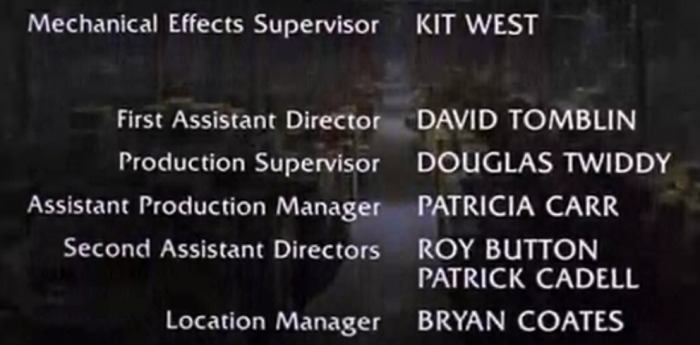
Nachspann aus "Jäger des verlorenen Schatzes"
weiß jemand ganz spontan welche Schrift das hier ist? Ich habe leider nur diesen Screenshot von YouTube, aber ich meine irgendwie, die Schrift zu kennen. Das "a" und das "d" sind durch ihren vom Stamm gelösten Bauch recht auffällig, oder? Ich bin sicher, das weiß jemand wie aus der Pistole geschossen (aus der Hüfte, natürlich).
Auch wenn ich's erwartet hatte, ich bin beeindruckt. Da lag ich übrigens falsch, von der Friz Quadrata hab ich noch nie gehört. Wahrscheinlich habe ich an irgendeine andere Schrift gedacht ...